2025 산돌 사이시옷: 타입 컨퍼런스의 주제는 '탐구하는 사람들'이었습니다. 이 주제를 행사 아이덴티티에 어떻게 녹일 수 있을지 많은 고민이 있었는데요. 수많은 시안을 거쳐 남은 건 '물음표'였습니다. 이 과정을 함께 살펴볼까요?
탐구를 어떻게 시각화할 수 있을까?
여러분은 '탐구'를 무엇이라고 생각하시나요? 저는 '탐구'가 어떤 개념이자 동시에 하나의 행위라고 생각했어요. 이를 시각화하는 가장 직관적인 방식이 무엇일지가 가장 큰 숙제였습니다.
처음에는 '탐구는 파고드는 것'이라는 아이디어로 디깅(digging)을 표현해 보기도 했고, 탐구하면 떠오르는 오브제로 그래픽 실험을 해보기도 했어요. AI 툴도 사용하며 가능한 한 많은 방향을 시도했습니다.
모든 시도가 와닿지 않았던 차에 ‘모든 탐구는 질문에서부터 시작된다’라는 문장을 떠올렸어요. 탐구는 결국 '무언가를 궁금해하는 마음'에 있고, 행사 주제를 관통하는 문구가 될 수 있을 것 같았죠. 그리고 물음표가 '탐구'를 상징적으로 드러내는 기호가 될 수 있다는 결론에 닿았습니다.
그리고 아주아주 많은 물음표를 그려보기 시작했는데요, 기준은 두 가지였어요.
첫 번째는 물음표를 해체하기입니다. 탐구는 단편적인 것이 아니라 여러 조각이 맞물려지는 것으로 생각했어요. 물음표를 최대한 많이 분해했고, 그 조각들을 패턴처럼 쌓아 조각보처럼 만들어보기도 했죠.
두 번째는 물음표인 듯 아닌 듯하게 그리기입니다. 최대한 다양한 형태의 물음표를 그리려면 큰 곡선의 몸체와 작은 점으로 찍히는 기존 구조를 벗어나야 했고, 그 과정에서 '물음표인가? 아닌가?' 헷갈리는 지점이 생겼어요. 나아가 물음표가 꼭 물음표처럼 보여야 하는 지에대한 논의로 이어졌죠. 오히려 그 모호함이 시각적인 재미를 주고, '탐구'라는 개념에도 더 가까워지는 듯했어요.
이렇게 해서 사이시옷 행사장에서 여러분이 보셨던 비주얼이 완성되었습니다. 어떻게, 이 물음표들이 ‘탐구의 이미지’를 잘 표현하고 있는 것 같나요?
이제는 적용할 차례
만들어진 비주얼을 어떻게 잘 보여줄 수 있을지에 대한 고민으로 이어지는데요. 행사 전반에 일관되게 노출되는 비주얼인 만큼, 적재적소에 잘 적용하는 것이 중요했죠.
행사장 공간에서 크게 보이는 요소들은 컬러를 세 가지로 고정했어요. 물음표가 아닌 조각난 일부만 보여주기도 하면서 강약을 조절했어요.
프로그램 북이나 손목띠를 전달하는 과정에서도 작은 재미 요소를 더했는데요. 현장 등록 시 참가자들이 '나의 탐구자 유형'을 선택할 수 있었고, 그 결과에 맞춰 스티커를 붙여 나만의 프로그램 북 표지를 완성하거나, 손목띠만 봐도 각 참가자의 유형을 알아볼 수 있도록 했어요.
컨퍼런스 쉬는 시간마다 플레이되던 모션그래픽은 조금 더 설명적인 방향으로 구성했어요. 'IT ALL BEGINS WITH A QUESTION’이라는 문구를 강조해서 보여주기도 하고, '탐구'하면 떠오르는 다양한 행위들을 추가로 그려 넣었죠. 물음표 자체가 이미 상징적인 기호이기 때문에, 어느 한 부분에서는 조금 더 친절하게 커뮤니케이션하고자 했어요.
또 다른 탐구, 「SD 초양」 견본집
사이시옷 첫 번째 세션은 산돌의 새로운 폰트, 「SD 초양」에 대한 강연이었는데요. 참석자분들이 행사 이후에도 내용을 복기하실 수 있도록, 체크인 키트에 「SD 초양」 스페시먼을 함께 담아 배포했습니다.
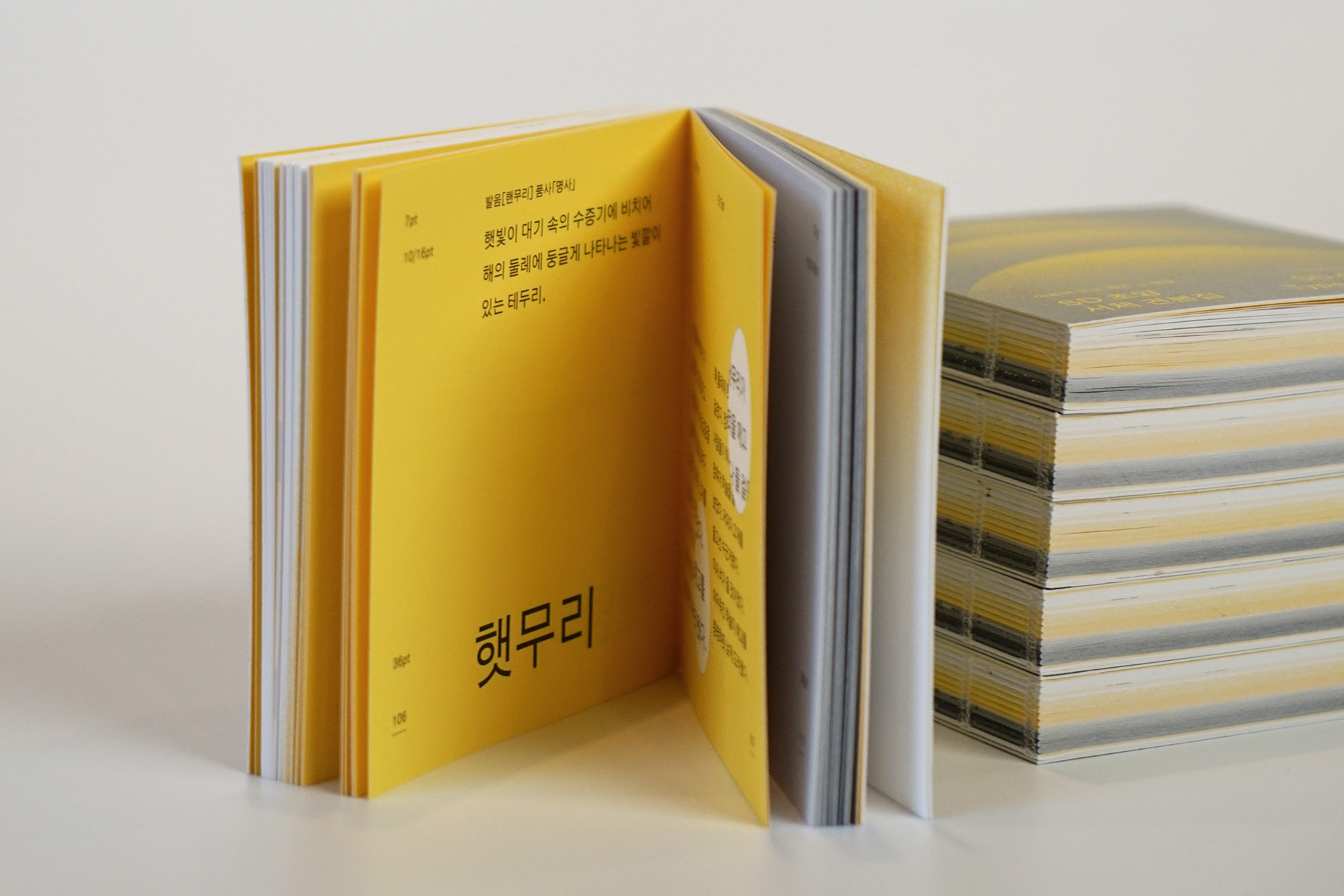
「SD 초양」은 1900년대 초 을유문화사에서 간행된 《조선말큰사전》의 한글 민부리 활자를 현대적으로 재해석한 폰트예요. 그 뿌리를 보여주고자 사전 형식을 빌려왔어요. 《조선말큰사전》이 사라져가는 한국어를 모은 것처럼, 우리는 사라져가는 순우리말을 모아보기로 했죠.
순우리말 중에서도 '해의 움직임 혹은 농도'와 관련된 단어들을 모았어요. '초양(初陽)'은 아침에 떠오르는 햇빛을 뜻하는데요. 《조선말큰사전》의 역사적 의미와 폰트의 따뜻한 인상을 고려해 붙여진 이름이라고 해요. 이 컨셉을 보여주기 위해 ㄱㄴㄷ 순이 아닌, 해가 뜨는 초양의 순간부터 해가 지고 난 새벽까지 시간순으로 단어를 배열했어요. 또 시간의 흐름과 배경에 따른 가독성 차이를 보여주기 위한 장치도 포함시켰어요. 표지와 슬리브는 해가 뜨는 순간을 그래픽으로 표현했어요. 본책이 빛나는 해라면 슬리브는 그 빛줄기처럼 보이도록 해, 책을 들어 올리면 해가 뜨는 장면처럼 보이기를 의도했답니다.
최근 폰트 트렌드는 짧은 시간에 많은 정보를 읽을 수 있도록 자폭이 좁은 편인데요. 「SD 초양」은 이와 달리 평체에 가까운 인상을 줍니다. 이는 「SD 초양」의 기본 구조에서 비롯돼요. 한 글자가 1,000×1,000 유닛 내에 있다는 것을 보여주고자 판형도 정사각형으로 설정했어요. 개인적으로 「SD 초양」은 라틴과 한글, 그 조합이 특히 아름답다고 생각했는데요. 한글과 영문을 함께 보여주는 페이지를 최대한 많이 넣으려고 레이아웃을 구성하기도 했어요.
초양이 가진 의미나 폰트 디자이너의 의도를 최대한 많이 담을 수 있도록 고민한 흔적이 받아보신 분들에게도 느껴지기를 바랍니다. 곧 출시되는 「SD 초양」, 여러분들의 후기도 정말 정말 궁금해지네요!